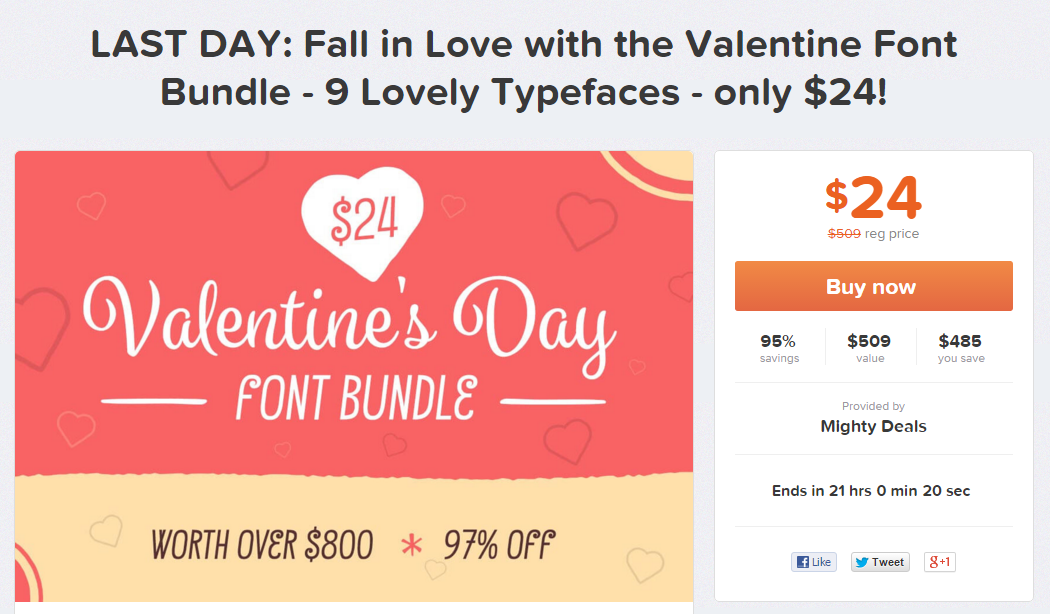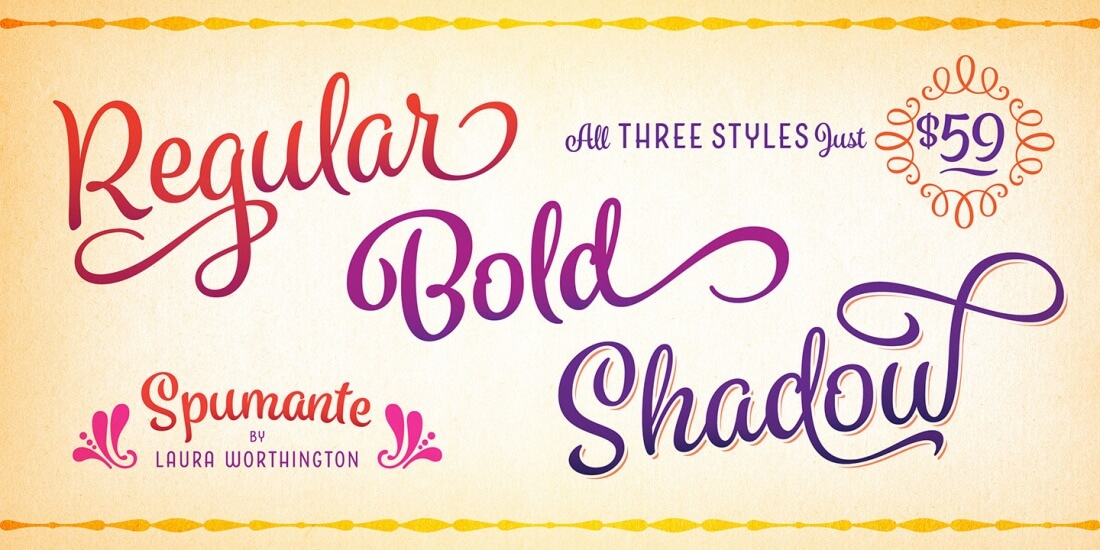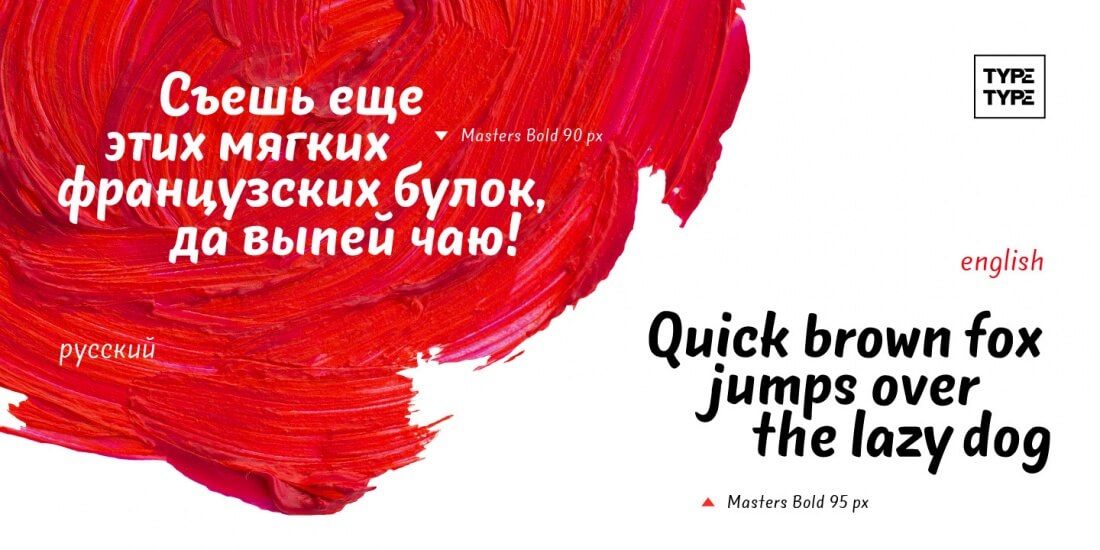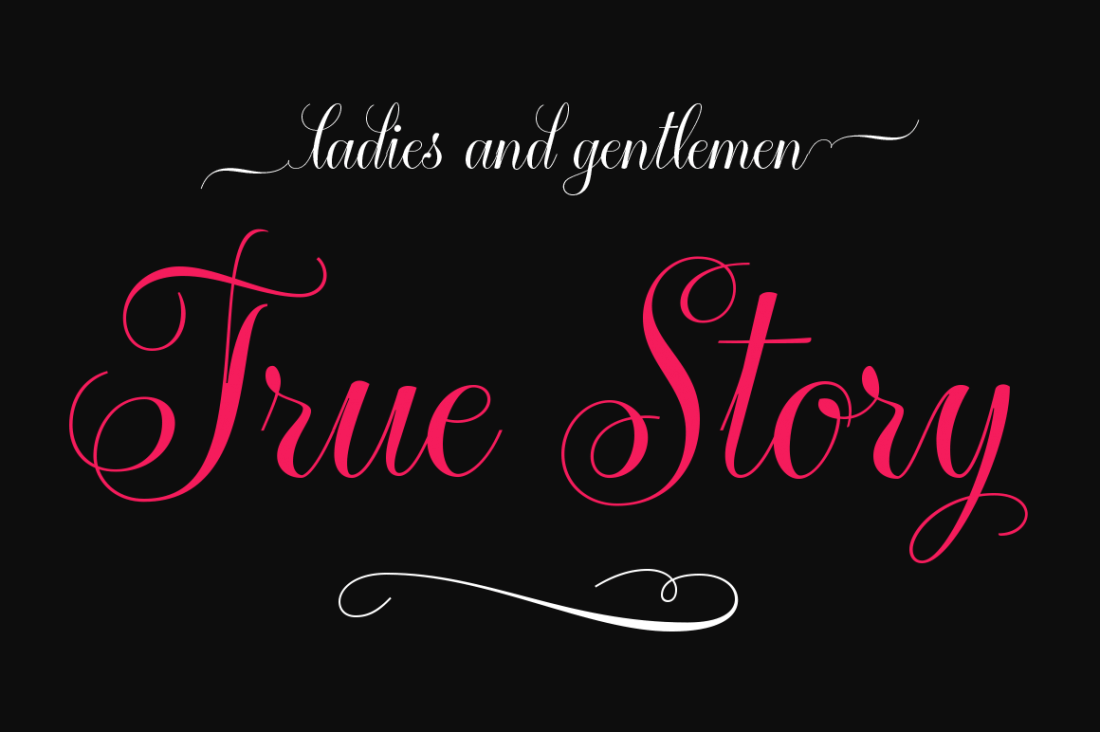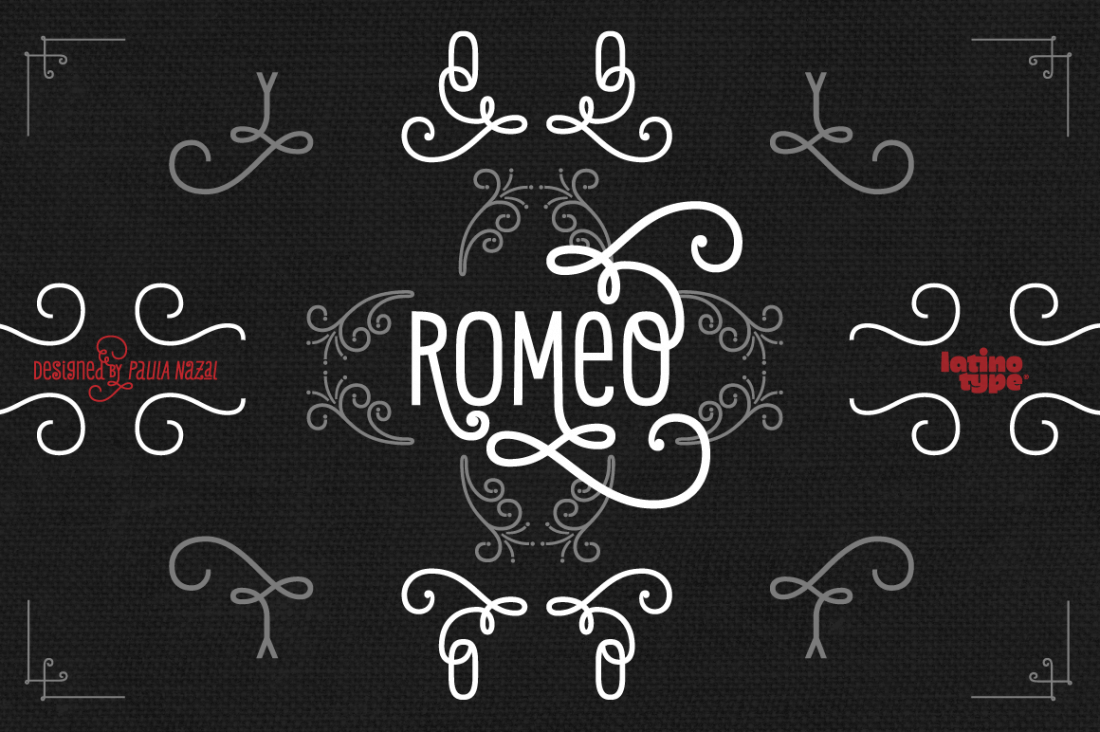
[Шрифт] 9 шрифтов для валентинок
Надо срочно сегодня! выкупать. 9 шикарных шрифтов. Скрипты для подарочных надписей к дню Св. Валентина.
Кроме обычного набора символов шрифты имеют дополнительно до 300 глифов с бантиками и завитушками.